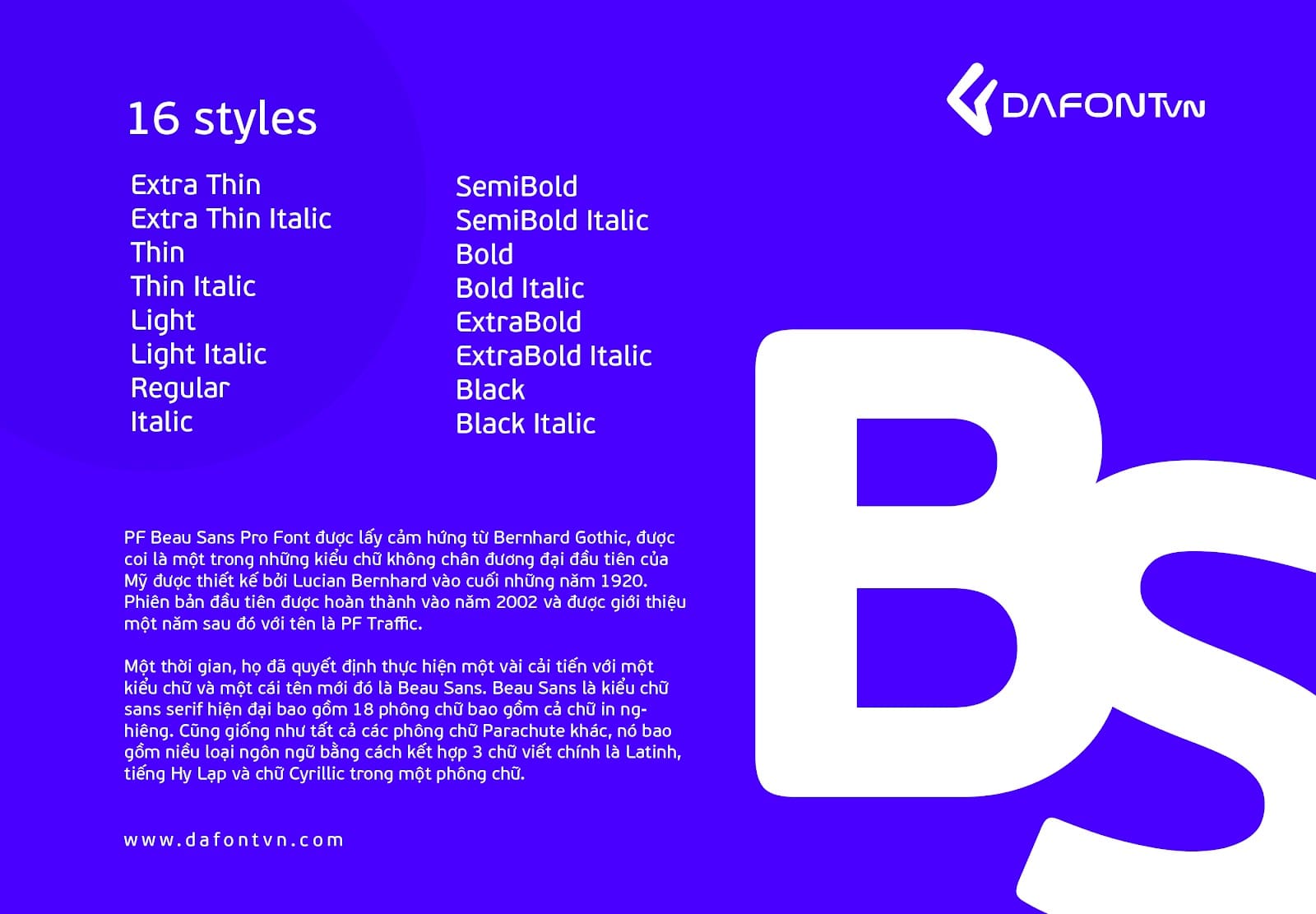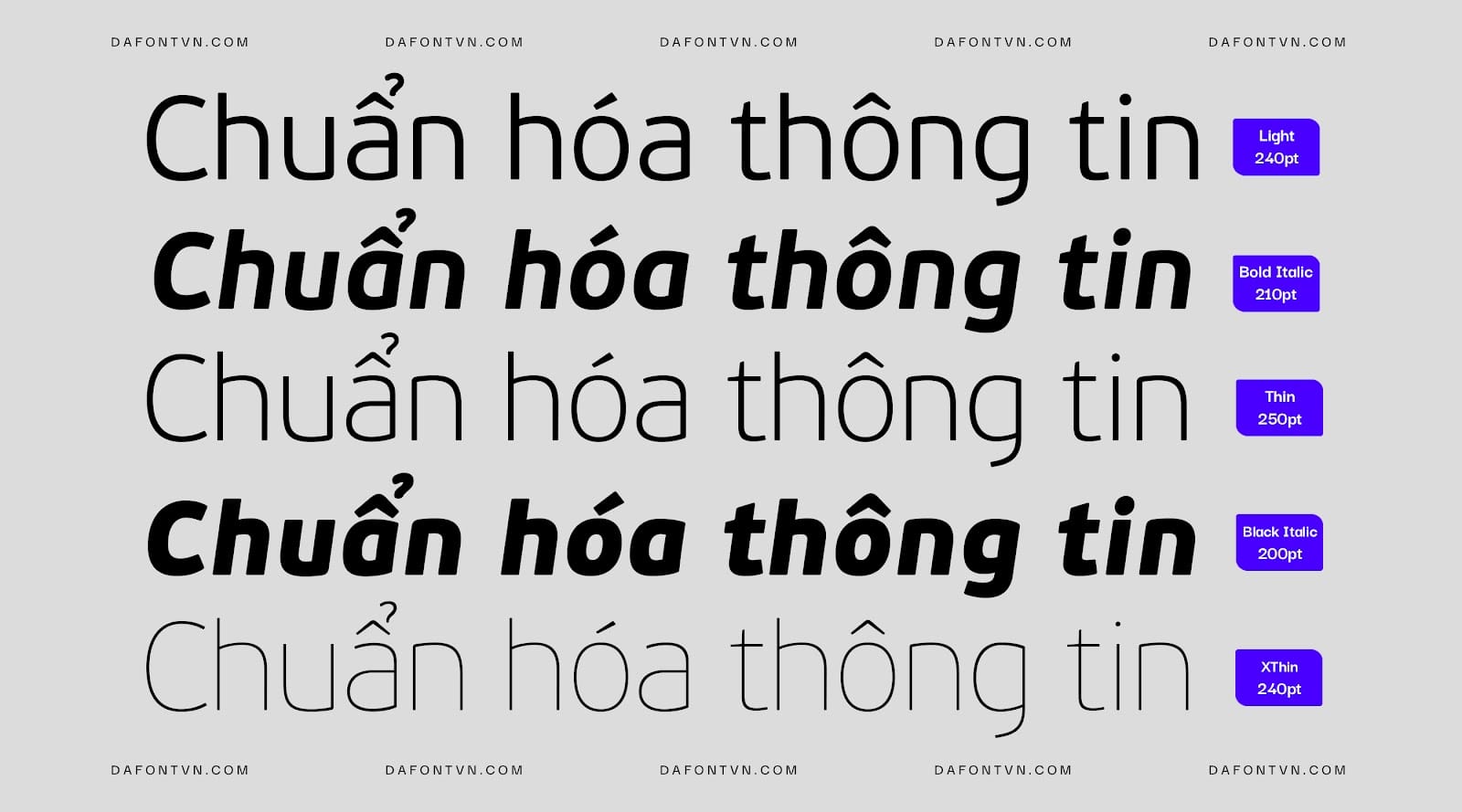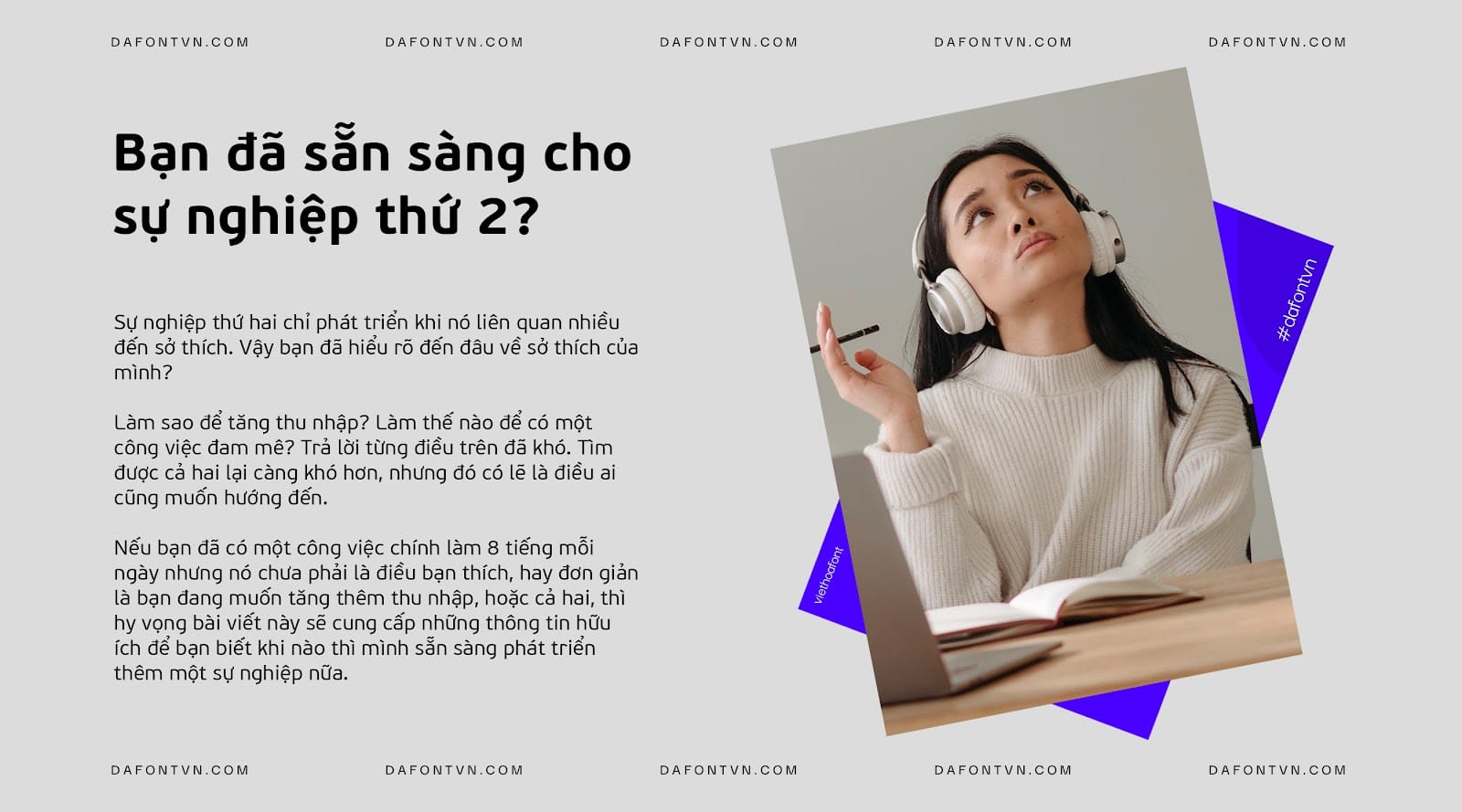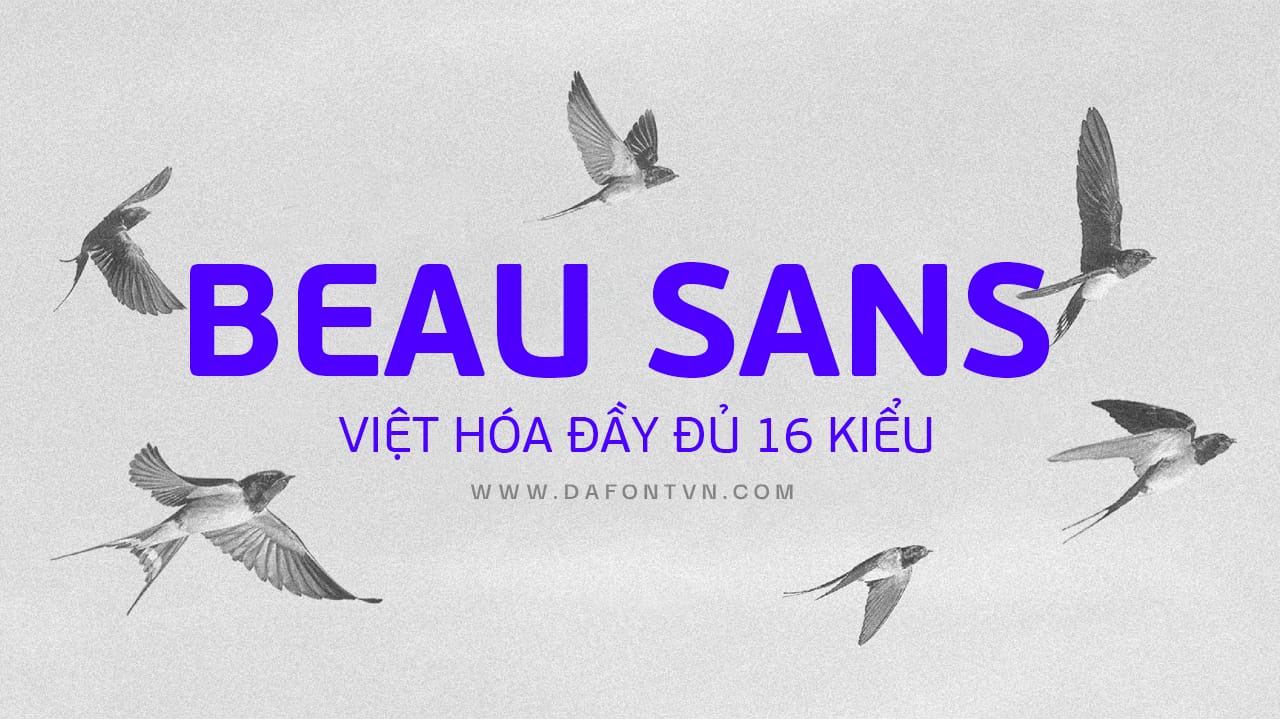
PF Beau Sans Pro Font được lấy cảm hứng từ Bernhard Gothic, được coi là một trong những kiểu chữ không chân đương đại đầu tiên của Mỹ được thiết kế bởi Lucian Bernhard vào cuối những năm 1920. Phiên bản đầu tiên được hoàn thành vào năm 2002 và được giới thiệu một năm sau đó với tên là PF Traffic.
Một thời gian, họ đã quyết định thực hiện một vài cải tiến với một kiểu chữ và một cái tên mới đó là Beau Sans. Beau Sans là kiểu chữ sans serif hiện đại bao gồm 16 phông chữ bao gồm cả chữ in nghiêng. Cũng giống như tất cả các phông chữ Parachute khác, nó bao gồm nhiều loại ngôn ngữ bằng cách kết hợp 3 chữ viết chính là Latinh, tiếng Hy Lạp và chữ Cyrillic trong một phông chữ.
Hơn nữa, mọi phông chữ trong bộ family này đã được hoàn thành với 145 biểu tượng không có bản quyền, một số trong số đó đã được một số tổ chức quốc tê đề xuất cho bao bì, khu vực công cộng, môi trường, giao thông, máy tính, đời sống đô thị.
Kiểu chữ Beau Sans hoàn toàn được khuyên dùng cho tiêu đề hoặc nội dung văn bản khi bạn muốn tạo bản sắc khác biệt và hiện đại cho một số sản phẩm hoặc dịch vụ. Mặc dù bộ font Beau Sans đã ra đời cách đây hơn 15 năm và có bản cập nhật năm 2021 nhưng cho đến nay đây vẫn là một trong những bộ font chữ được sử dụng rất phổ biến trong đó Viettel đang sử dụng bộ font chữ này cho nhận dạng thương hiệu của mình trong các thiết kế như ấn phẩm, banner, poster, quảng cáo, truyền thông, ứng dụng và trang web.